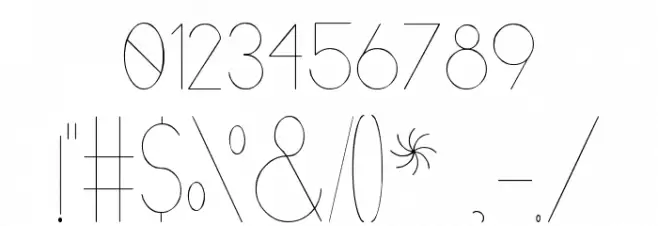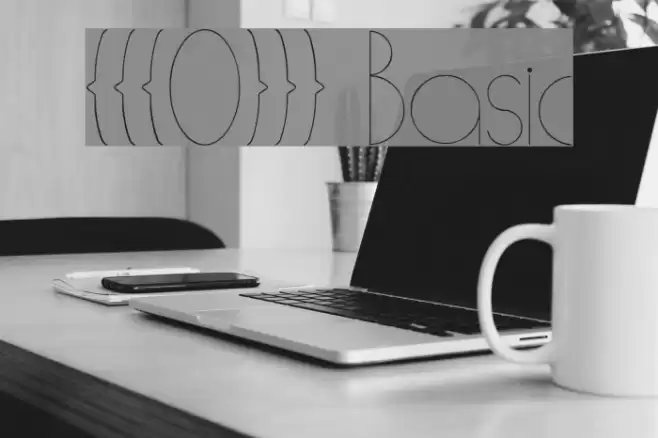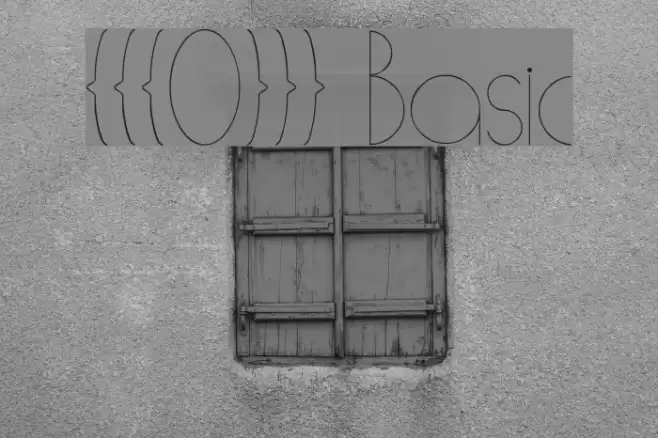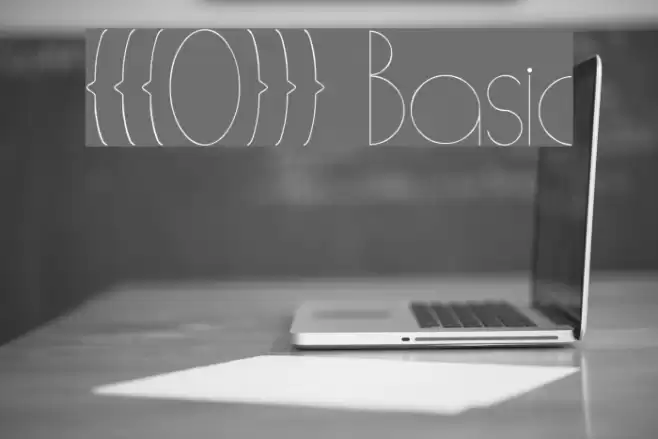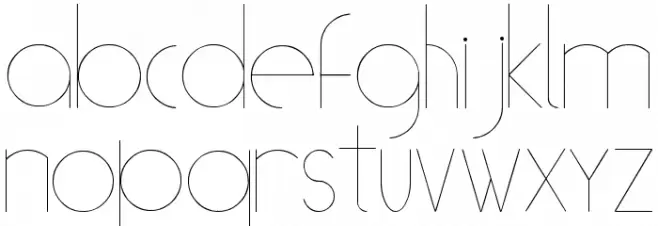
[[[O]]] Basic Font
✎ Sans Serif
O-BASIC Groß
O-BASIC Kleinbuchstaben
O-BASIC Anderer Schreiben
| Vorgeschlagene Projekte | Ideal for fashion branding, luxury product packaging, modern art posters, and minimalist web design. |